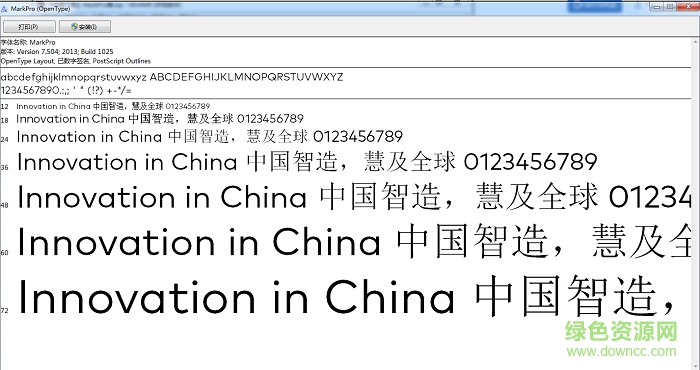
markpro字體
ff mark pro字體是一套免費(fèi)的英文字體,線條纖細(xì),簡(jiǎn)潔美觀,十分有時(shí)尚感,常常用在雜志設(shè)計(jì)或平面設(shè)計(jì)方面,喜歡的小伙伴快來下載吧!
無襯線體介紹
無襯線體(Sans-serif)專指西文中沒有襯線的字體,與漢字字體中的黑體相對(duì)應(yīng)。與襯線字體相反,該類字體通常是機(jī)械的和統(tǒng)一線條的,它們往往擁有相同的曲率,筆直的線條,銳利的轉(zhuǎn)角。無襯線體在 80 年代開始興起,在當(dāng)時(shí)被稱為 Grotesque(荒唐的)或 Gothic(哥特的),因?yàn)樘烊坏募夹g(shù)感和理性氣質(zhì),無襯線字體多為科技型企業(yè)所青睞。隨著「簡(jiǎn)約美」理念開始風(fēng)行,1957 年上市的 Folio、helvetica 和 Univers 三個(gè)極具代表性的無襯線字型開始成為當(dāng)代字型的主流。